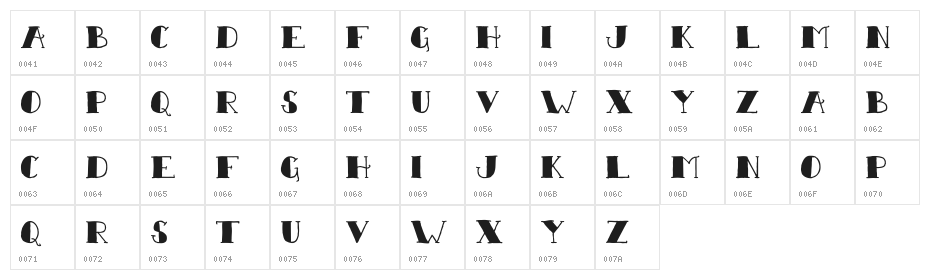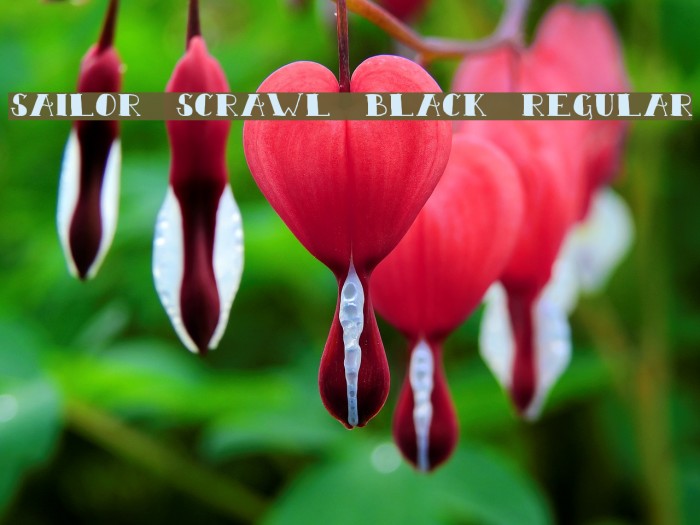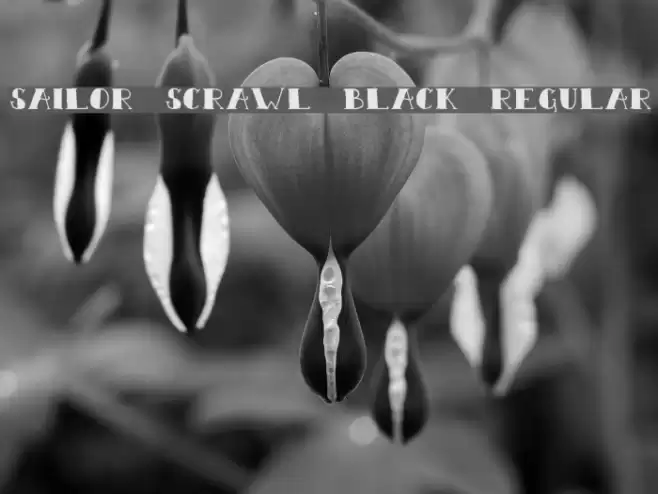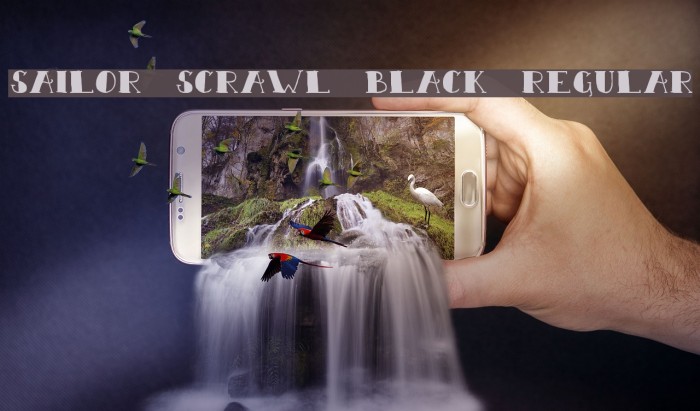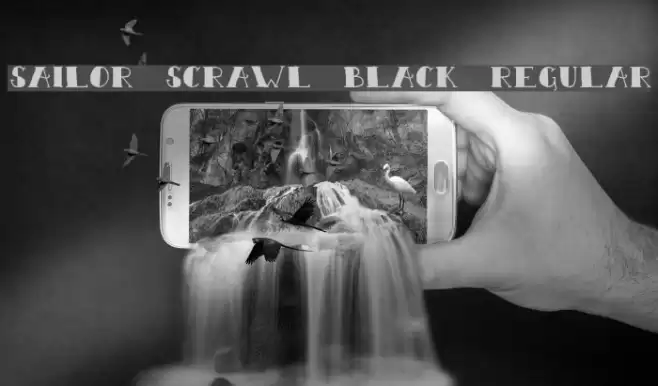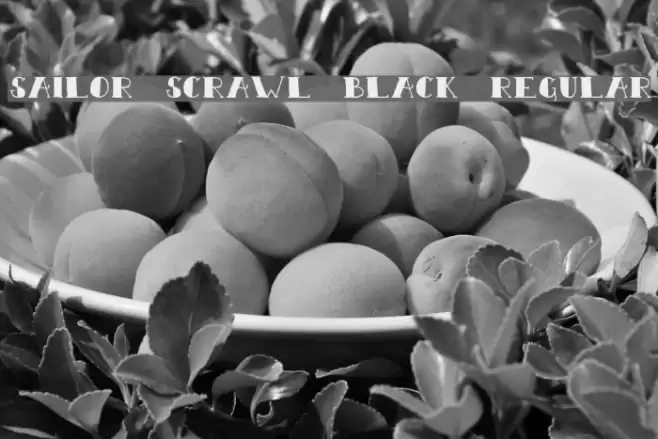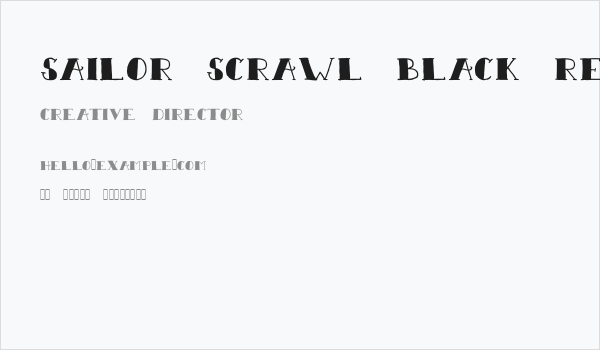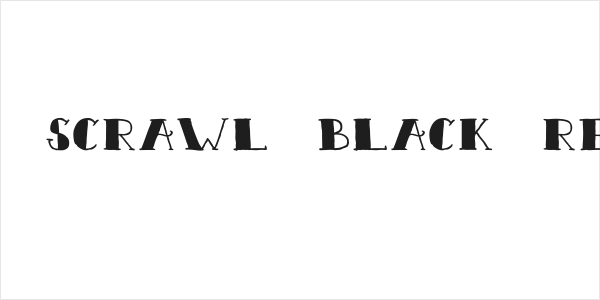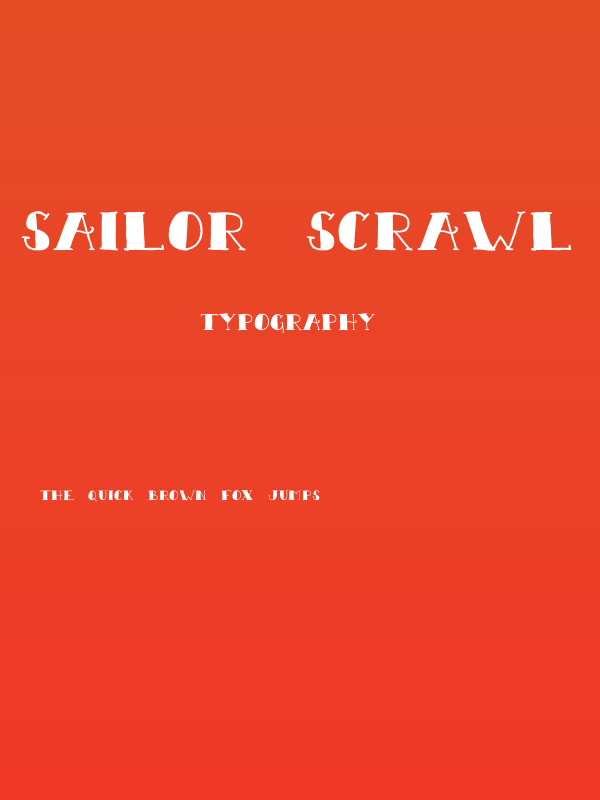
Sailor Scrawl Black Regular Font
| Gesamtstil | Vintage |
| Vorgeschlagene Projekte | Ideal for tattoo designs, vintage posters, nautical-themed branding, and creative headlines. |